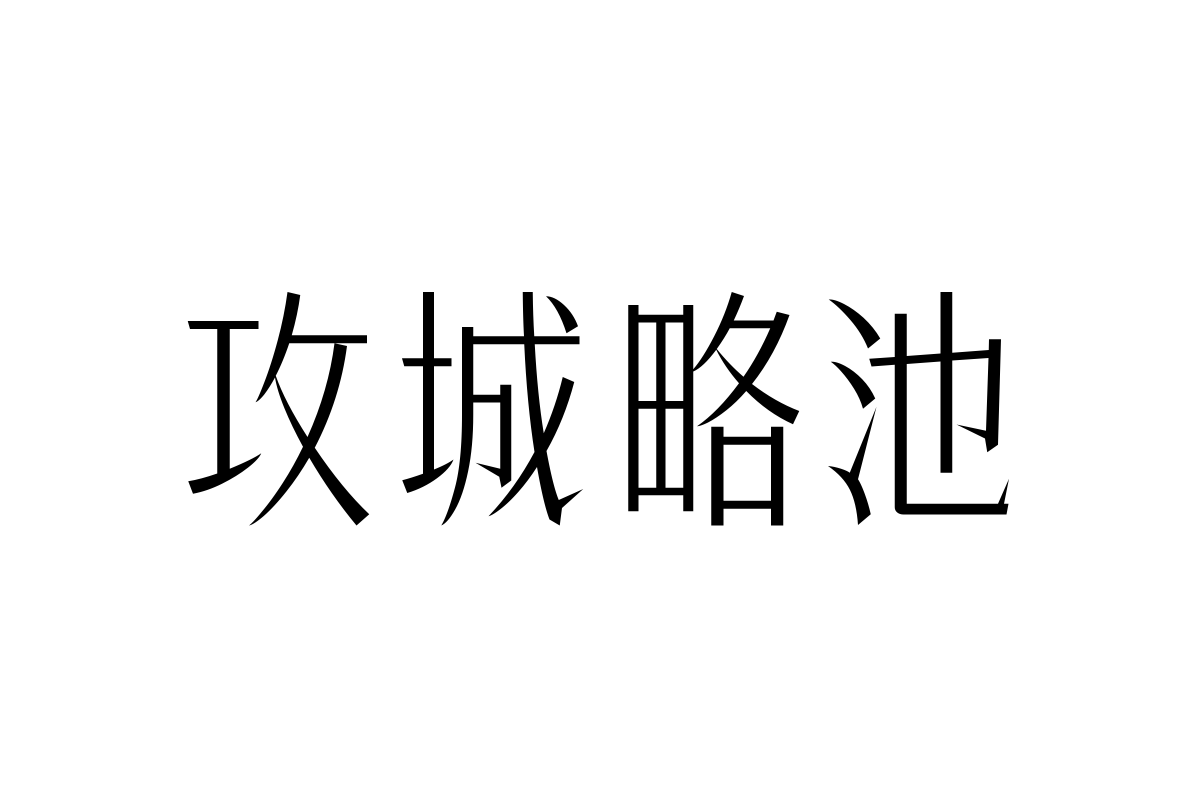
三极锐宋黑简体是一套专为中文书写设计的无衬线字体,其特点是笔画清晰,结构简洁。这款字体适用于需要清晰易读的文本排版,如标题、正文等。它的设计灵感来源于传统书法和现代平面设计的结合,使得字体既有传统书法的韵味,又不失现代感。
在字形上,三极锐宋黑简体采用了简洁的线条,使得整个字体看起来既美观又实用。它的笔画粗细适中,既不过于粗犷也不过于纤细,适合用于各种类型的文本排版。
此外,这款字体还具有一定的可扩展性,可以根据需要进行个性化调整,以适应不同的设计需求。无论是用于书籍、杂志还是网页设计,三极锐宋黑简体都能展现出独特的魅力。